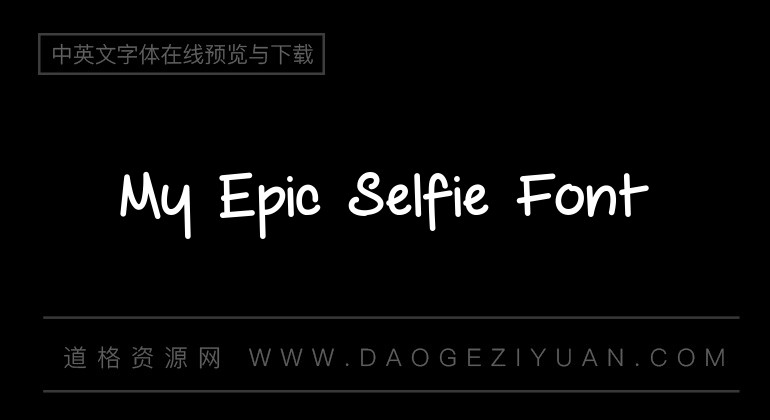
My Epic Selfie Font
My Epic Selfie Font是一种手写风格的字体,它的设计风格类似于人们在社交媒体平台上发布的自拍照片(也称为“自拍”或“自拍照片”)。这种字体具有轻松、自然和时尚的感觉,适合用于各种印刷和数字媒体设计项目,如海报、广告、社交媒体图像、博客、网站和T恤设计等。 My Epic Selfie Font具有多种字形和特殊符号,包括斜体、粗体、下划线、断词符号和符号等。这种字体的特殊符号和图形可以让设计师更轻松地创建惊人的设计效果,增强品牌形象和吸引目标受众。 总之,My Epic Selfie Font是一种多功能和独特的字体,适合各种设计项目,能够增强您的设计作品的品牌形象和视觉吸引力。
My Epic Selfie Font是一款非常不错的手写艺术字体,具有很好的视觉感,适合于文化类的宣传设计、商业类品牌的广告和产品包装设计以及个性化文字排版等较多场景。